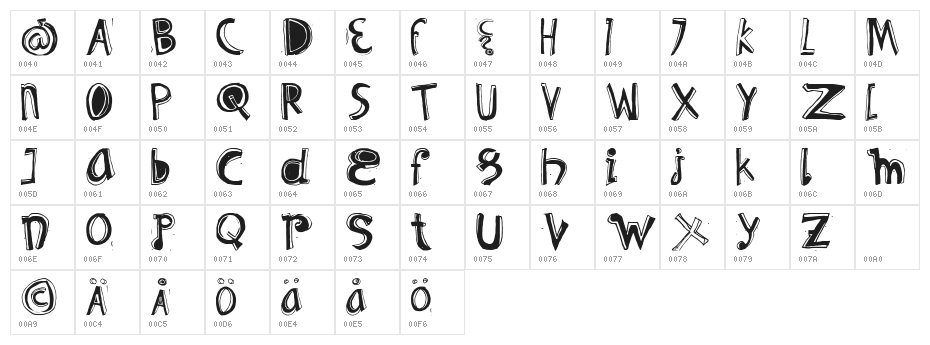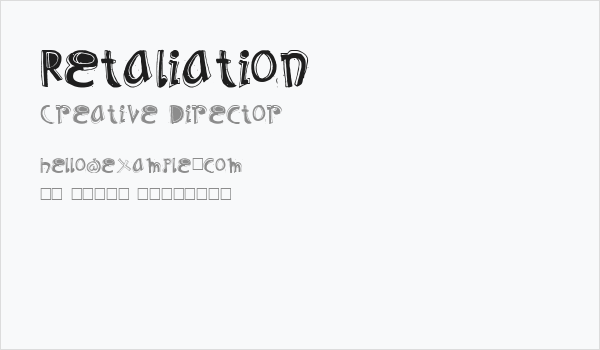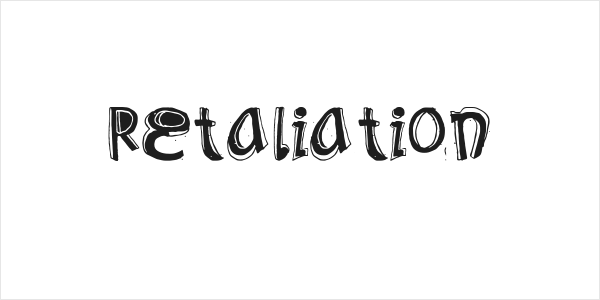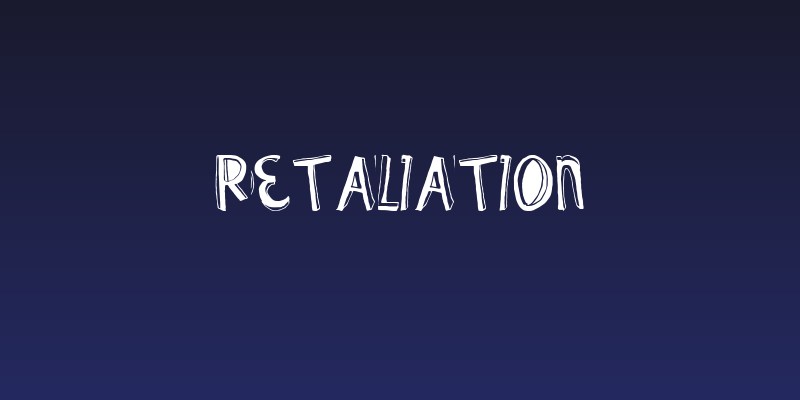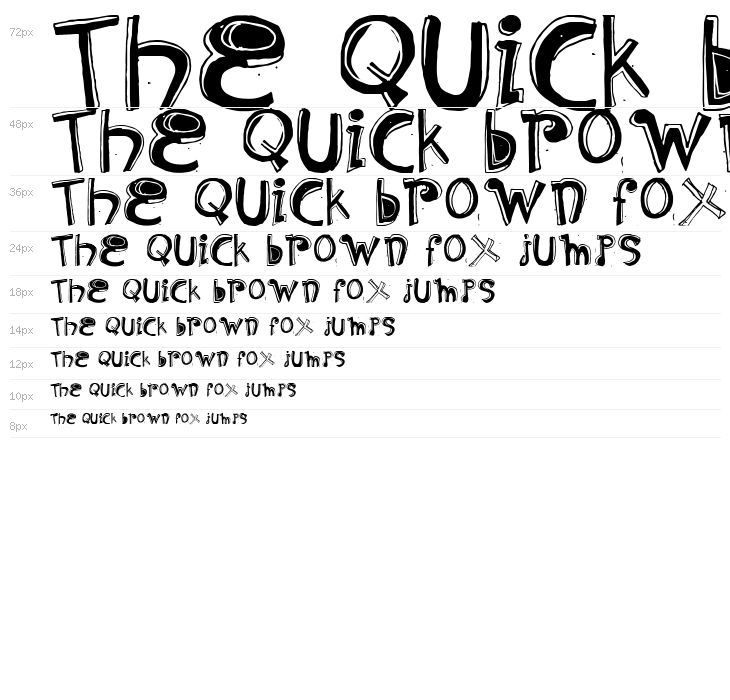
Retaliation Font
| おすすめプロジェクト | Ideal for creative projects such as children's books, greeting cards, posters, and branding for playful or artistic brands. |